Hacklife
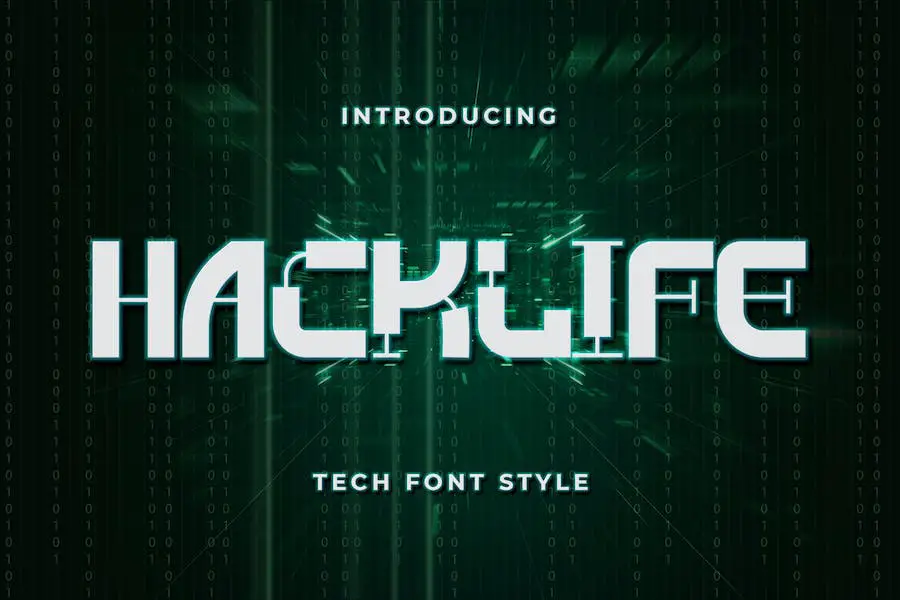
Hacklife to inspirowana technologią czcionka o futurystycznym charakterze, idealna do przeniesienia pomysłów projektowych o tematyce technologicznej lub komputerowej na wyższy poziom.
Dzięki eleganckiemu i nowoczesnemu wyglądowi jest to idealny wybór dla grafików, którzy chcą ulepszyć swoje projekty i nadać im wyrazisty i nowatorski wygląd.
Niezależnie od tego, czy pracujesz nad stroną internetową, logo, czy jakimkolwiek innym projektem, unikalny styl Hacklife sprawi, że Twoja praca będzie wyróżniać się z tłumu.
Cyber
„Przedstawiamy „Cyber”, najlepszą czcionkę komputerową do wszystkich Twoich projektów. Niezależnie od tego, czy jesteś grafikiem pracującym nad plakatem science-fiction, tworzącym zaawansowane technologicznie logo, czy projektującym futurystyczny nagłówek strony internetowej, ta czcionka idealnie nadaje się do dodania nowatorskiego akcentu do Twojej pracy.
Jedną z wyróżniających się cech „Cyberu” jest jego wszechstronność. Dzięki eleganckiemu i nowoczesnemu wyglądowi nadaje się do szerokiej gamy projektów, od czcionek komputerowych Google po czcionki komputerowe Adobe.
Niezależnie od tego, czy pracujesz w programie Word, Canva, Circuit czy Figma, ta czcionka bezproblemowo integruje się z dowolną platformą, co czyni ją niezbędnym narzędziem dla każdego projektanta.
LiniaTech
LineTech to elegancka i futurystyczna czcionka internetowa, idealna dla grafików chcących ulepszyć swoje projekty. Dzięki trzem różnym wersjom – Bold, Regular i Light – ta czcionka zapewnia wszechstronność i elastyczność.
Jego czyste linie i nowoczesny design sprawiają, że idealnie nadaje się do zastosowania w branży technologicznej, naukowej, internetowej i komputerowej. Niezależnie od tego, czy potrzebujesz wyróżniającego się tytułu, czy efektownego monogramu w logo, LineTech zapewni Ci wsparcie.
Maztech
Maztech to idealna czcionka komputerowa dla grafików chcących ulepszyć swoje projekty.
Ta czcionka technologii wojskowej dodaje futurystyczny akcent do każdego projektu, dzięki czemu nadaje się do różnych celów, w tym do logo, brandingu, plakatów science-fiction, opakowań produktów, zaproszeń, reklam, branży gier, filmów i innych futurystycznych projektów typograficznych.
Jego unikalny i robotyczny styl z pewnością przyciągnie wzrok widzów. Niezależnie od tego, czy pracujesz nad dokumentem programu Word, projektujesz w serwisie Canva, tworzysz obwody czy korzystasz z Figmy, Maztech jest czcionką niezbędną, która wzmocni Twoją kreatywność.
Łańcuch techno
Techno Chain to elegancka i futurystyczna czcionka komputerowa, która może przenieść Twoje projekty projektowe na wyższy poziom. Idealna do logo, opakowań, reklam, czasopism i nie tylko, ta czcionka z łatwością dodaje odrobinę wyrafinowania i stylu.
Jego wszechstronność pozwala płynnie uzupełniać szeroką gamę kreatywnych pomysłów, czyniąc je naprawdę wyjątkowymi.
Niezależnie od tego, czy pracujesz nad starymi projektami komputerowymi, nowoczesnymi, eleganckimi układami, projektami inspirowanymi kaligrafią, czy też projektami technologicznymi i futurystycznymi, Techno Chain to doskonały wybór. Dzięki eleganckiej i przyciągającej wzrok estetyce z pewnością zrobi wrażenie.